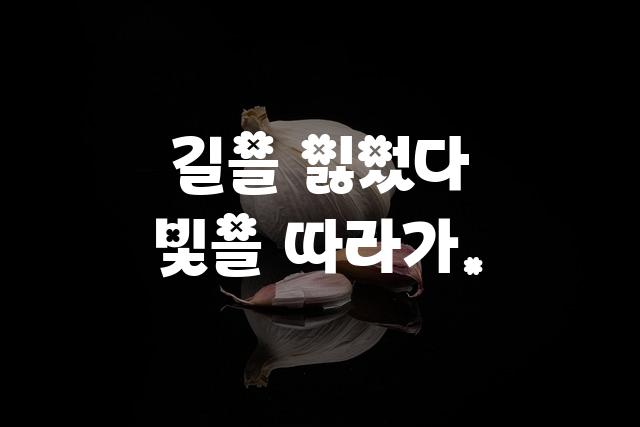
Y이드스트릿체는 (주)케이티에서 제작한 꽉 찬 고딕과 장식적인 요소가 가미된 고딕 폰트입니다. 가로로 긴 글자 형태가 특징이며, 현대적이면서도 독특한 매력을 제공합니다.
Y이드스트릿체은(는)
기본 고딕, 두꺼운 스타일, 굵은 고딕, 장식 스타일, 단단함, 별모양/패턴 계열의 생김새를 가지고 있으며
광고 캠페인, 디지털 광고, 소셜 미디어 등에서 자주 활용되며, 효과적인 메시지 전달에 적합합니다.
이 폰트는 광고/마케팅, 크리에이티브, 엔터테인먼트 분야에 잘 어울리며,
친근한, 창의적인, 재미있는 느낌을 담고 있는 것이 특징입니다.